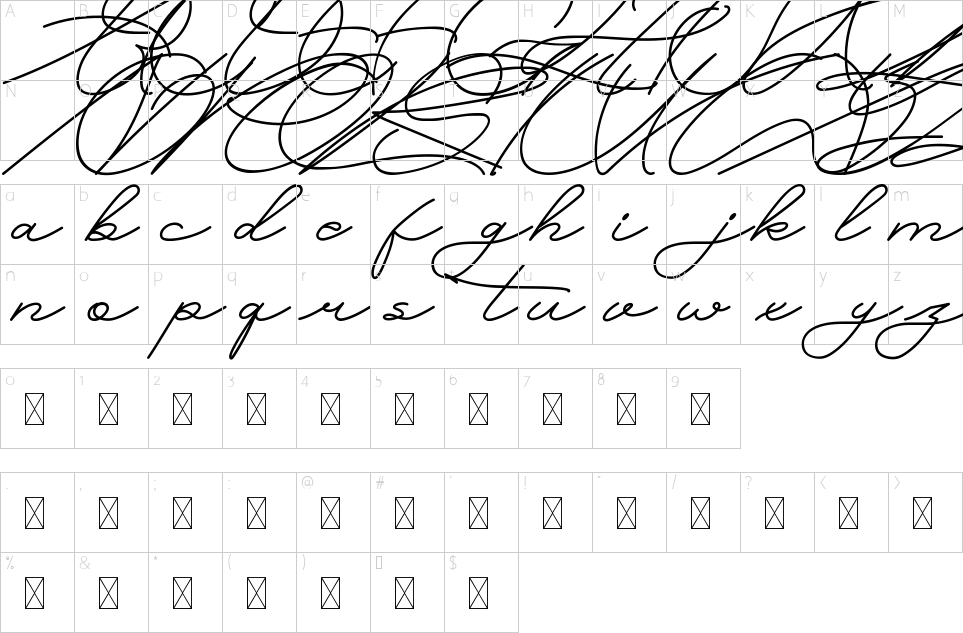
Aqui está uma versão curta e envolvente da descrição para a página de download da fonte ‘Glow Overload Font – 1001 Free Fonts’: Glow Overload é uma fonte que transborda de elegância e emoção, adequada tanto para textos formais quanto para design gráfico vibrante. Inspirada em estilos artísticos modernos, esta fonte oferece uma aparência única e fluida, ideal para decorar sites, flyers ou até mesmo trabalhos acadêmicos de forma criativa. Desenvolvida pela designer desconhecida chamada CalligraphyFonts, Glow Overload é um recurso gratuito que combina facilidade de uso com qualidade. Desde seu lançamento, o design se destacou entre os usuários, sendo baixado 3.270 vezes. Se você está procurando uma fonte vibrante e autêntica para enriquecer seus projetos em qualquer plataforma (Windows ou Mac), Glow Overload é perfeito. Composto de letras fluidas e linhas contínuas, esta fonte traz vida e energia a suas criações, tornando-a uma opção inteligente para designers que buscam algo diferente e inspirador.